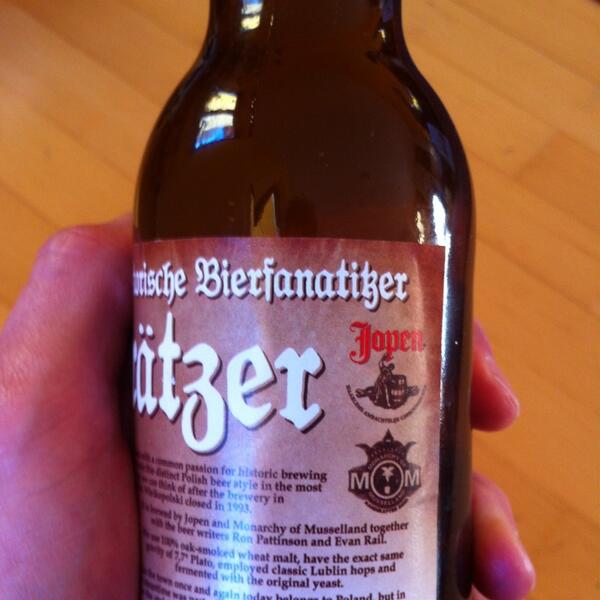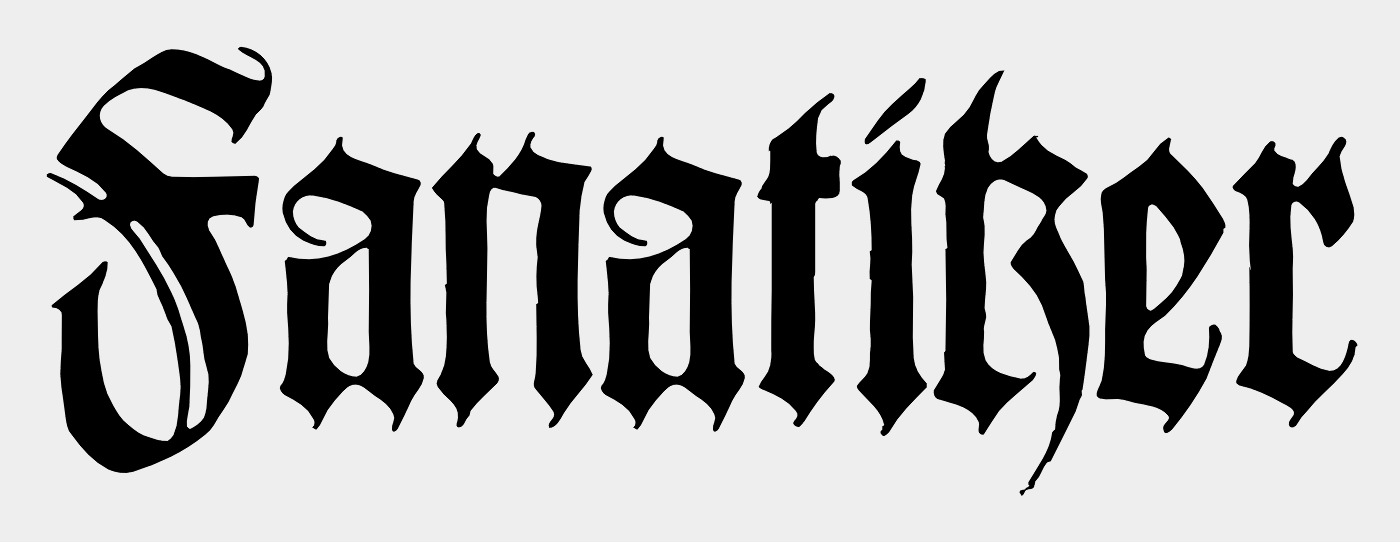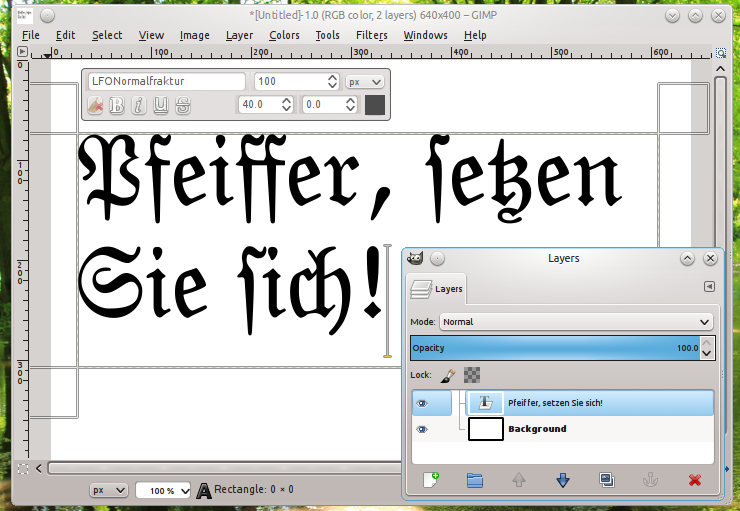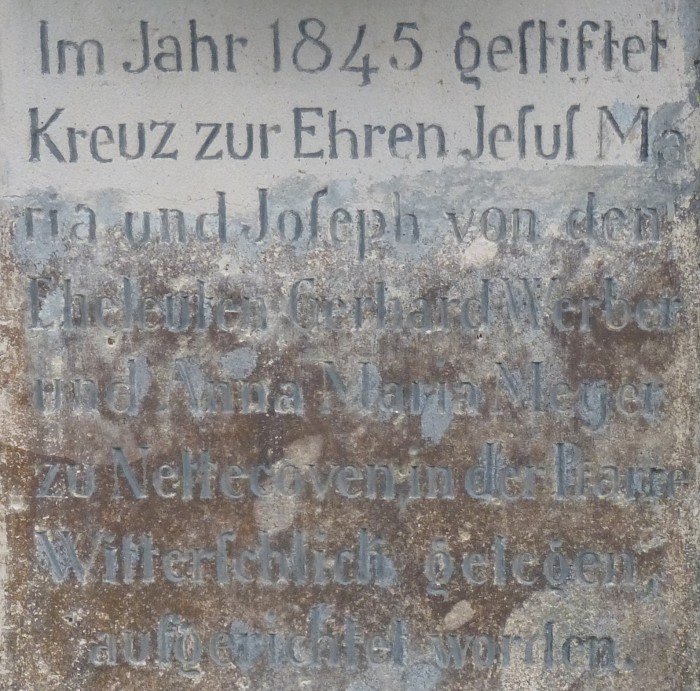
Neue Rechtschreibung?
Ich würde den Ast ja gerne als absteigend erleben, denn dann ist es ja ein leichtes, alle schon erstellten Schriftarten in einem Rutsch mit OpenType-Ligatur-Tables nachzurüsten, da ja durch die Vorarbeit mit dem UNZ-Zeichensatz alle in diesem Bereich über den gleichen Zeichenvorrat verfügen, und die Glyphen auch gleich benannt sind. Dann einmal die Liga-Lookups zu bauen, dauert vielleicht einen Nachmittag, und das dann in die verschiedenen Fonts zu kopieren, einen weiteren. Ich werde mit mal die Testversion des aktuellen Office ansehen, in wie weit das dann auch funktioniert. Allerdings werde ich kaum die Nutzer der dann „legacy“Programme im Regen stehen lassen, und es dann zusätzlich an bei der Codierung belassen, so lange der Ast noch Blätter trägt.
Derzeit ist der Ast aber eben noch sehr stark, und verdammt aufrecht, denn ich werde wohl kaum empfehlen Word, nur weil es OpenType in Grenzen unterstützt dann zur Erstellung von Grafiken zu empfehlen, denn hier unterstützt weder CorelDRAW noch Xara Studio noch Canvas OpenType. Quark auch nicht, von OpenSource-Lösungen wie Inkscape, Gimp, Blender, My‹Paint mal zu schweigen.
Und wenn man dann, wie nicht selten geschehen das ſ einfach über historische Formen zuschltet, kommt so etwas heraus:
(ein Beispiel von einer Microsoft-Seite)
Quark unterstützt erweitere Opentype-Funkionen.
Serif Page unterstützt erweitere Opentype-Funkionen.
CorelDraw unterstützt erweitere Opentype-Funkionen.
Auf dem Mac unterstützt das wirklich kostengünstige Mellel erweitere Opentype-Funkionen.
Welche archaische Versionen hast Du denn noch am Start?
Dass viele Opensource-Programme keine erweiterte Opentype-Funktionalitäten bieten, ist enttäuschend, zumal viele Betriebssysteme die Renderfunktionalitäten mitbringen (AAT unter OSX, WPF unter Windows, Freetype unter *nix, welche Plattform auch immer Bitstreams Panorama). Dann gibt es noch Graphite, von dem ich aber wie bei AAT nicht weiß, wie kompatibel zu OTF die Engine ist.
Also mein Gimp kann Autoligaturen (die durch Bindehemmer bei Bedarf auch ordnungsgemäß unterdrückt werden). Das reicht, um »ordentlich« Fraktur zu schreiben. Ganz normal, ohne jede Hilfsmittel.
Neben Abiword scheint auch LibreOffice mittlerweile einfache OpenType-Ligaturen zu unterstützen – und mehr braucht es ja gar nicht. Allerdings variiert das Resultat (anders als bei Firefox oder XeTeX) noch je nach OS und das Sperren funktioniert noch nicht richtig.
Und die Unterstützung für „UNZ-Software“ ist ja im Vergleich dazu noch viel schlechter, da auf Windows beschränkt.
Allerdings werde ich kaum die Nutzer der dann „legacy“Programme im Regen stehen lassen …
Das verlangt ja auch keiner. Dass man OpenType-Glyphen, die für eine OpenType-Ersetzung vorgesehen sind, als Notfallvariante zusätzlich noch mit einem Unicode-Wert versieht, ist ja relativ banal und wird schon seit der Einführung dieses Font-Formates so gehandhabt.
Strittig ist, dass hier eine »zukunftsweisende Lösung« entsteht. Die vermeintlichen Vorteile (einheitliche Tastaturtreiber, problemlose Wechselbarkeit der Fonts etc.) greifen ja auch erst dann, wenn die UNZ-Belegung einmal zum De-facto-Standard geworden ist und wirklich 9 von 10 Schriften im Umlauf und auf den Rechnern der Anwender so belegt sind. Bis das der Fall ist, ist es ja sogar noch eine zusätzliche Belegung, die erst einmal noch mehr Inkompatibilität der verfügbaren gebrochenen Schriften schafft.
Wenn dann in 15 bis 20 Jahren die Umstellung vollzogen ist, haben wir eine »Lösung«, die keiner mehr braucht (weil dann Smartfont-Unterstützung wohl Standard sein wird) und wir haben PUA-Texte, die nicht mit herkömmlichen Texten kompatibel und entsprechend verarbeitbar sind. Daher wird hier angezweifelt, ob man wirklich in diese Zukunft »investieren« sollte oder sich nicht lieber gleich für die saubere Lösung entscheidet und diese entsprechend fördert.
Mir scheint es ja bei einigen (hier nicht mitdiskutierenden) ja auch eher so, als ob UNZ auch wieder so eine demonstrative Geschichte ist, die sich gar nicht allein an der technischen Praktikabilität und Zukunftstauglichkeit misst. Für den Rest der Welt ist es ja ein klarer Vorteil, dass ein c-ZWJ-h im Zweifel einfach als c-h dargestellt wird, wenn die Ligatur nicht angezeigt werden kann. Für den eingefleischten Frakturverfechter ist das ja aber Blasphemie! Man sieht in den Ligaturen den einzig richtigen Stand deutschen Schriftsatzes und keine Option, die bei mangelnder technischer Unterstützung mehr oder weniger auf Antiqua-Satz zurückfällt. Die Frakturligaturen (insbesondere die Zwangsligaturen) werden als Quasi-Buchstaben betrachtet und man will sie daher auch als kodierte Einzelzeichen durchdrücken. In einem UNZ-Werbetext ist ja sogar die Rede davon, dass diese Belegung ein Anfang sein könnte, diese Zeichen generell (also auch im Antiqua-Satz) wieder in der Bevölkerung etablieren zu können. Da geht es dann also augenscheinlich um mehr als bloße technisch optimale Lösungen.
Das verlangt ja auch keiner. Dass man OpenType-Glyphen, die für eine OpenType-Ersetzung vorgesehen sind, als Notfallvariante zusätzlich noch mit einem Unicode-Wert versieht, ist ja relativ banal und wird schon seit der Einführung dieses Font-Formates so gehandhabt.
Wobei es übrigens bei einigen Programmen besser funktioniert, der durch OpenType eingesetzten Glyphe keinen Unicode-Wert zuzuweisen und dafür einen PUA-Klon der Glyphe zu erstellen. Zumindest in einigen Programmen kann man nur so erreichen, dass man beim Markieren des Textes im endgültigen PDF auch die Ursprungszeichen erhält und nicht den PUA-Code der Ligatur. (Keine Ahnung, ob das durch einen Standard geregelt ist, aber es geht ja eh um einen Notbehelf.)
Und am Rande: Inkscape kann schon seit einigen Jahren standardmäßig aktivierte OpenType-Features.
Mir sieh diese Unsaubere Kantenführung einzig als das Ergebnis eines Autotracings aus. So eine Schrift zaubere ich in 2 Stunden hin, würde das aber so nicht mal als Freefont anbieten, aber ich habe schon noch schlimmeres gesehen, für das jemand Geld haben möchte,
Restaurierungspatzer oder Werk eines Praktikanten™?
(Ich beziehe mich auf »Jeſuſ«.)